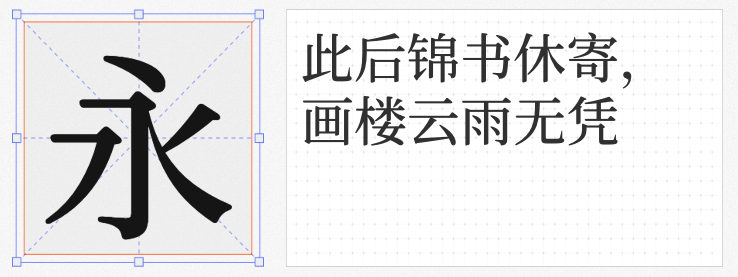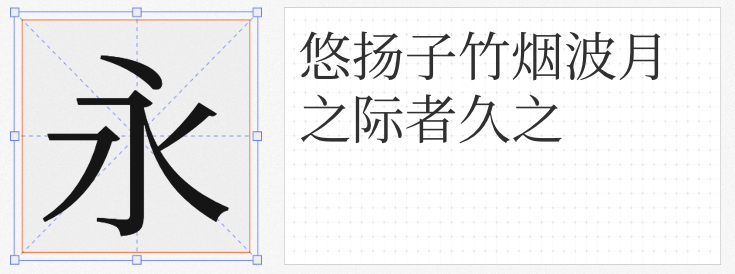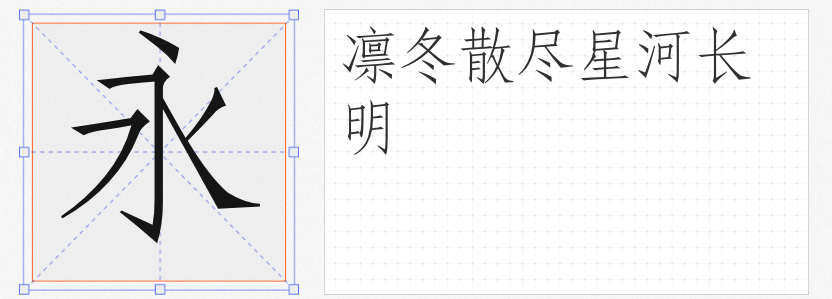
在海报设计的视觉语言中,字体是传递情感与信息的关键载体。宋体因其端庄雅致的气质,始终是中文排版的核心选择。本文精选四款免费商用宋体,兼顾传统韵味与现代适配性,助您轻松打造兼具美感与实用性的海报作品。
1. 香萃等粗宋
香萃等粗宋以平滑柔和的笔画起收与转角,赋予字体温暖的视觉触感。其略紧的中宫结构在保持严肃性的同时,通过重新设定的横竖比例与局部改良,显著提升屏幕显示清晰度。无论是大型户外广告还是移动端海报,均能呈现清朗温润的排版效果。传统印刷中,其人文气息更能让文字与画面自然融合,成为文化类海报的理想之选。
2. 汉字之美仿宋GBK 免费
这款字体脱胎于宋版书刻本,将楷书笔意与宋体结构完美融合。笔画粗细均匀、字身修长,起落顿挫间透出欧柳楷书的刚柔并济。其方正字形与均匀间隔,既保留老宋字的严谨,又通过横斜竖直的现代处理提升可读性。适合历史主题、文化展览等需要古典气质的海报设计,单字使用亦可作为点睛之笔。
3. 昭源宋体 Regular
作为昭源黑体的配套宋体,昭源宋体以现代感设计突破传统框架。其丰富的字重选择与超大收字量,可满足从标题到正文的多元需求。开源特性支持商业项目无障碍使用,在印刷品中展现精致细节,在数字屏幕上保持清晰锐利。搭配昭源黑体使用,更能形成视觉层次,适合科技、商业类动态海报。
4. 寒蝉锦书宋 Medium
基于思源宋体改良的寒蝉锦书宋,通过添加圆角与重构字重比例,打造出更易阅读的温润字形。其均衡的粗细变化与排版优化,让长文本海报也能保持视觉舒适度。“锦书”之名暗含“锦上添花”的祝福,特别适合教育、公益类海报传递温暖关怀,亦可作为品牌标语的特色字体。
这四款宋体各具特色,无论追求人文温度、古典韵味、现代效率还是阅读体验,均能提供专业级解决方案。设计师可根据项目调性自由搭配,让文字成为海报中不可或缺的美学符号。